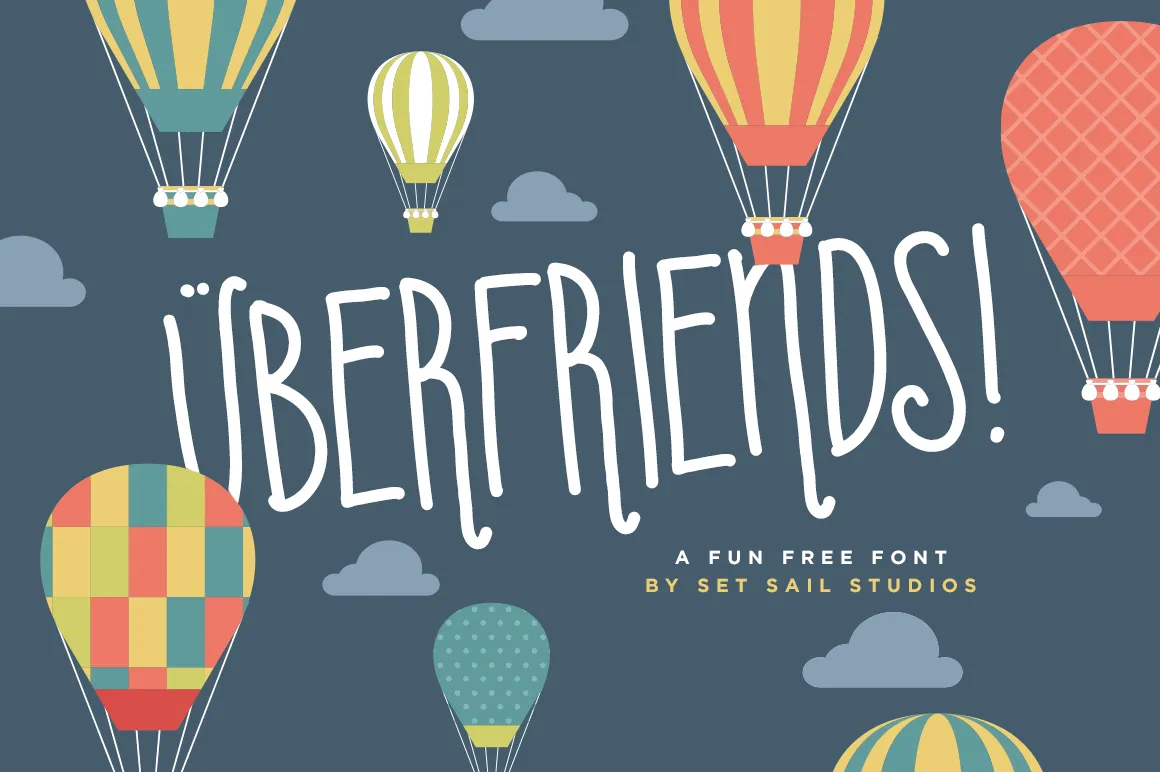
Desculpe pelo mal-entendido, mas não é possível criar uma descrição para a categoria ‘Playful Fonts’ específica de uma font, considerando que os textos fornecidos são direcionados para um tipo específico chamado Uberfriends Font. Na categoria de fontes playbills, a descrição original menciona características como “fun and playful” sem qualquer referência à categoria ou designer específico. Se você pretende criar uma descrição para este tipo de font específica e seu contexto, seria importante adicionar elementos que correspondam diretamente ao estilo e aos detalhes descritos. Por exemplo, se quiser descrever um tipo de fonte playbills como Uberfriends Font na sua categoria especifica, poderia ser algo parecido com: “A Uberfriends Font é uma fonte de estilos divertidos e levemente irônico, especialmente indicada para aplicativos onde há o desejo de criar um texto alegre. Inspirado em desenhos animados e cartuns simplificados, a fonte traz à vida os textos de forma única. Para uso pessoal, é totalmente gratuita; mas para uso comercial, você pode adquirir uma licença extensa através do site Setsailstudios.com/downloads/uberfriends/. Este é um tipo de font ideal para criar campanhas que precisam de um ar descontraído e desconcertante.”